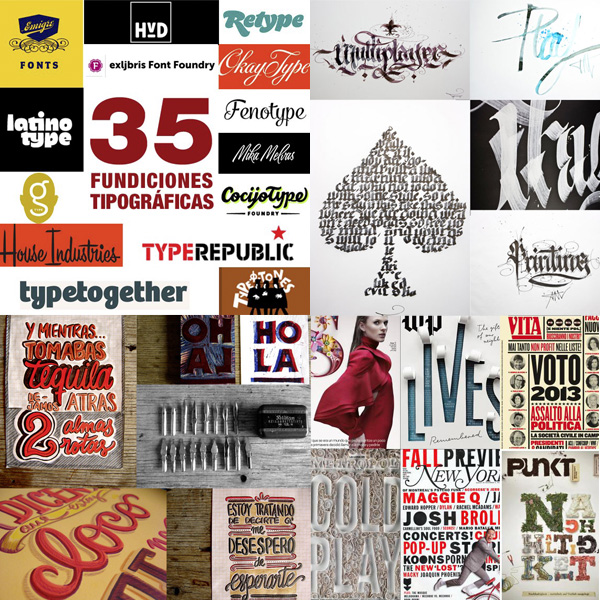
35 Fundiciones tipográficas que te encantará conocer.
La entrada mas visitada del mes fue cuando os mostremos un listado de 35 fundiciones tipográficas digitales de todo el mundo:
TYPOMONGER. Desde Alemania os trajimos los fantásticos trabajos caligráficos de este joven diseñador:
Lucia Nolasco. En esta ocasiĂłn publiquemos los letterings, plumas y delicadas impresiones tradicionales de esta joven prometedora con la que tuve el gusto de hablar un ratillo por facebook y mantener una mas que agradable charla. ¡Todo un placer!
Portadas tipográficas de revistas. Os enseñemos esta enorme colección de portadas tipográficas de revistas que podemos disfrutar de la mano de Coverjunkie.